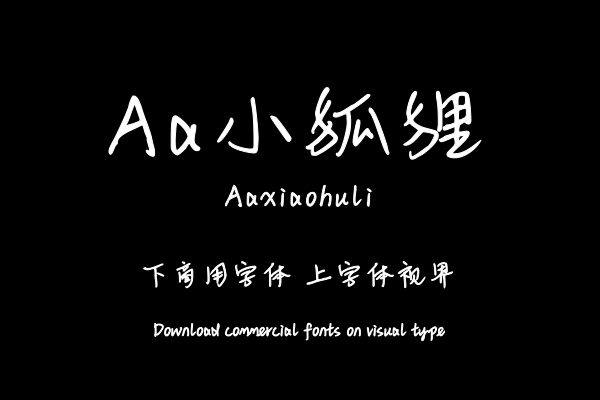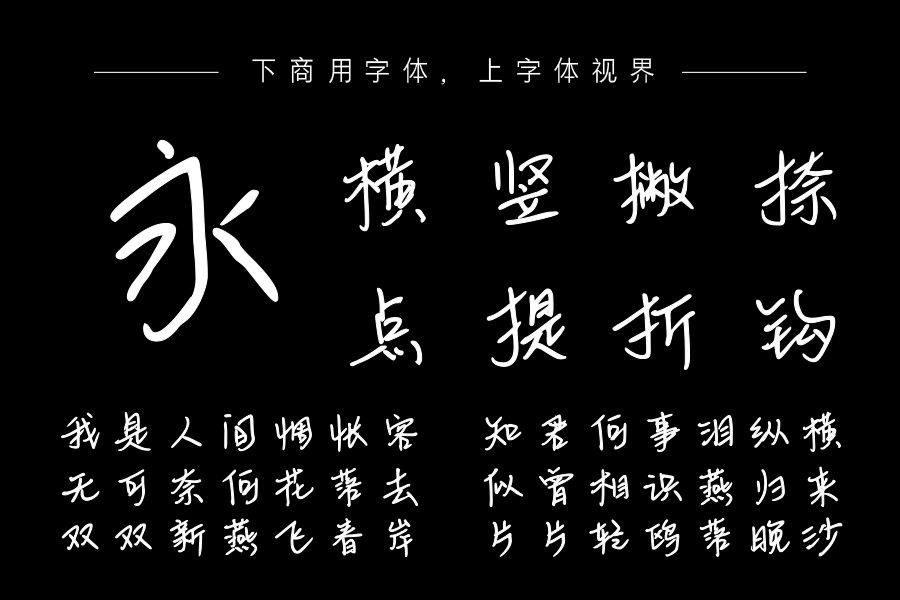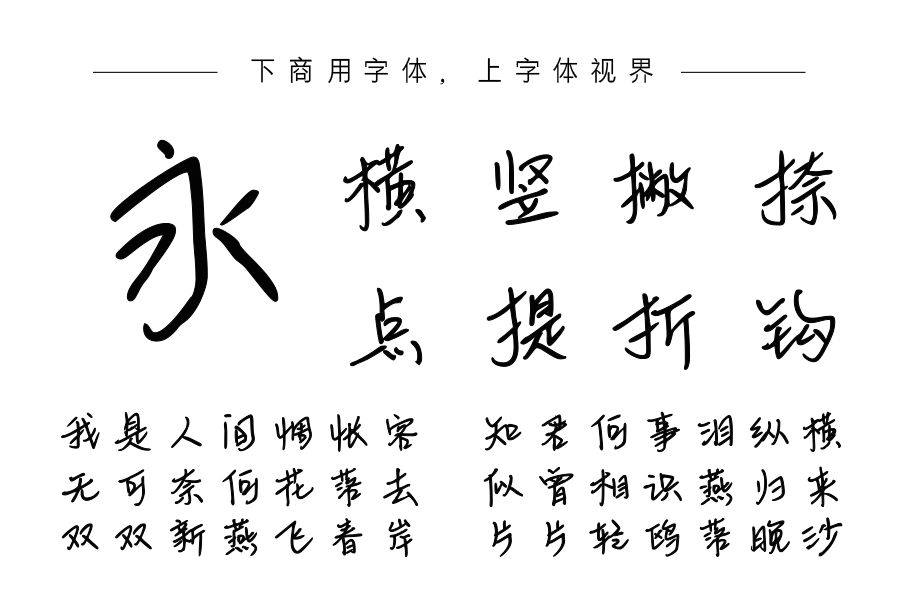
Aa小狐狸是一款手写体,书写灵活、笔画自然。字形优雅洒脱,是一款风格独特的手写字体。作为标题正文均可,适用场景广泛。购买须知:“下载服务费”与“字体VIP”所获得字体 仅用于个人非商用, 商用请联系付费授权。本字体为电脑用字,手机没有root权限不支持直接手机换字(手机如何root,请自行百度搜索教程)。购买前请先 了解清楚后再付款 ,字体为虚拟产品无法回收 一旦购买不支持退款。